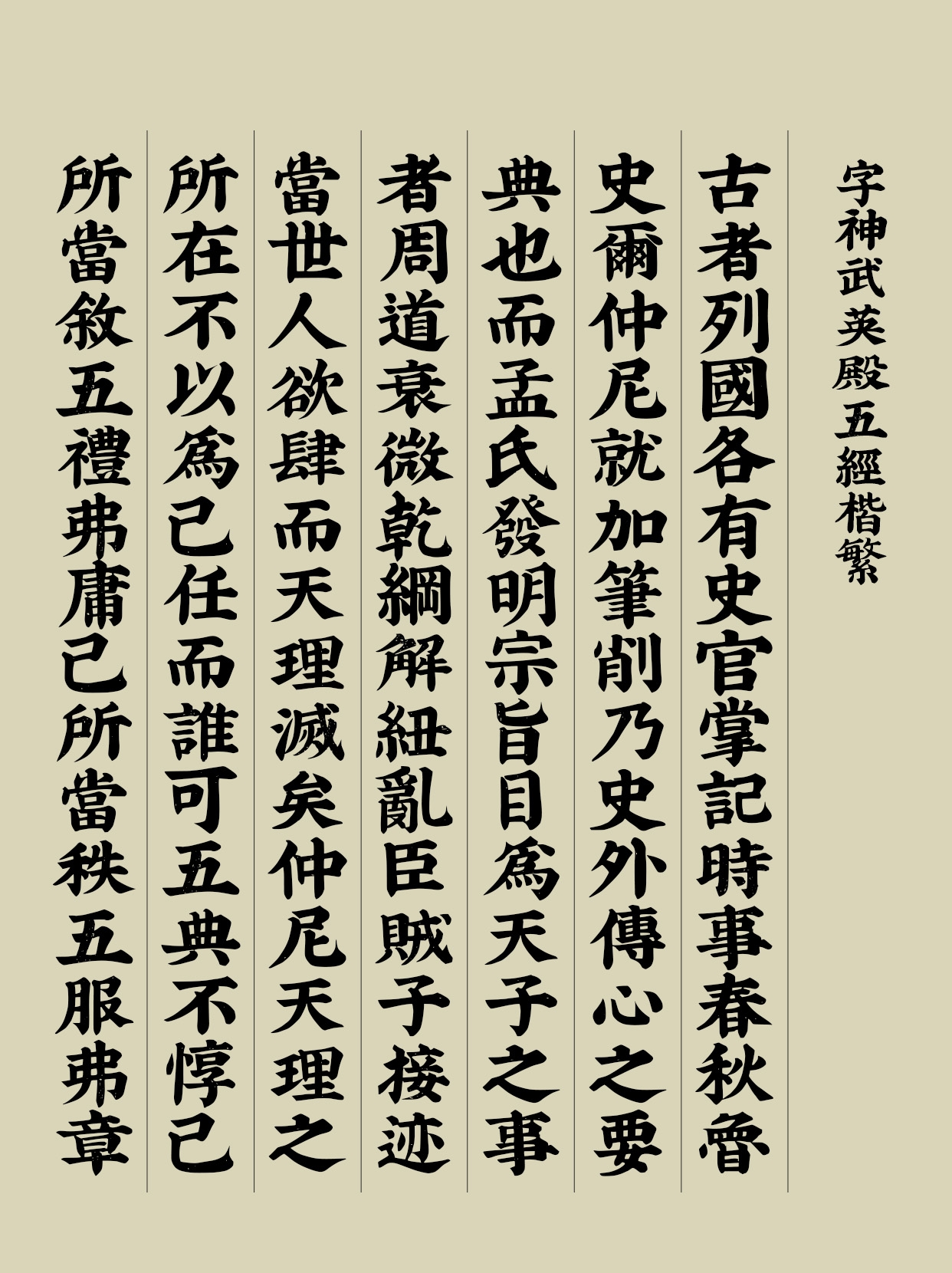
字神武英殿五经楷繁
God-WujingT
經典閱讀類字體
《五经魁本大字》是明代嘉靖三十一年(1552年)由学者翁溥校刊的一部重要儒家经典合集。该版本因字体硕大、刊印精良而被誉为“魁本”,其版刻文字端庄雄健、结构疏朗,笔划兼具金石刀法的锐利与书写的古拙气韵,体现了明中期仿宋刻本追求恢弘气象的典型审美,为现代字体设计提供了汲取传统刻本美学精髓的典范。 “字神武英殿五经楷家族”以翁溥校订的魁本大字《五经》为蓝本,收录BIG5、GBK、常用香港粤语字符集等编码范围,满足香港、台湾、大陆等多地区简繁不同汉字写法与字数范围的要求。遵循 “方正端庄、重心居中” 的框架,字形规整呈矩形,尽显经典典籍的严谨法度;线条粗重饱满且粗细均匀,采用利落直角勾勒轮廓,笔画连接处清晰断开,复刻出雕版印刷 “刀刻般” 的利落质感;通过字形大小如钱的设计与均匀的间距排布,呈现出庄重典雅、力透纸背的视觉特质,还原明代仿宋版书的风貌。适合应用于古籍复刻整理、传统文化学术出版、儒家经典传播、古典主题海报设计、非遗文化衍生品等场景。